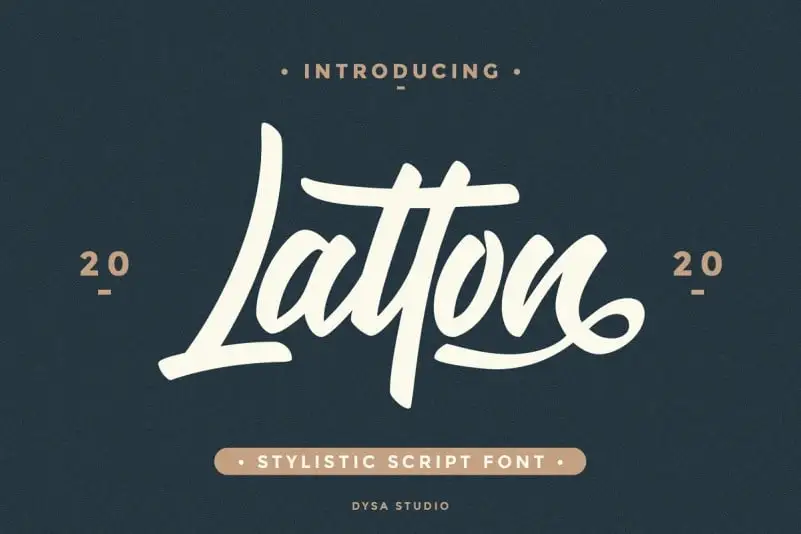
Latton Brush Font – Download Grátis
A Latton Brush Font é uma delicada e fluente tipografia feita à mão que traz uma característica única muito grossa e elegante. Esta outra coleção de tipo script perfeita para seus projetos de marca, excelente para “logotipo”. A Latton tem bordas suaves, o que dá um estilo autêntico e trabalhado à mão a este font. Seja você uma designer ou criativo digital, esta font será uma escolha ótima. Perfecto para aqueles que buscam dar um toque pessoal aos seus projetos de design. A Latton Brush Font é uma fonte perfeita para qualquer projeto, seja logotipo, logo ou apenas adicionar um toque autêntico e sofisticado a sua identidade visual.